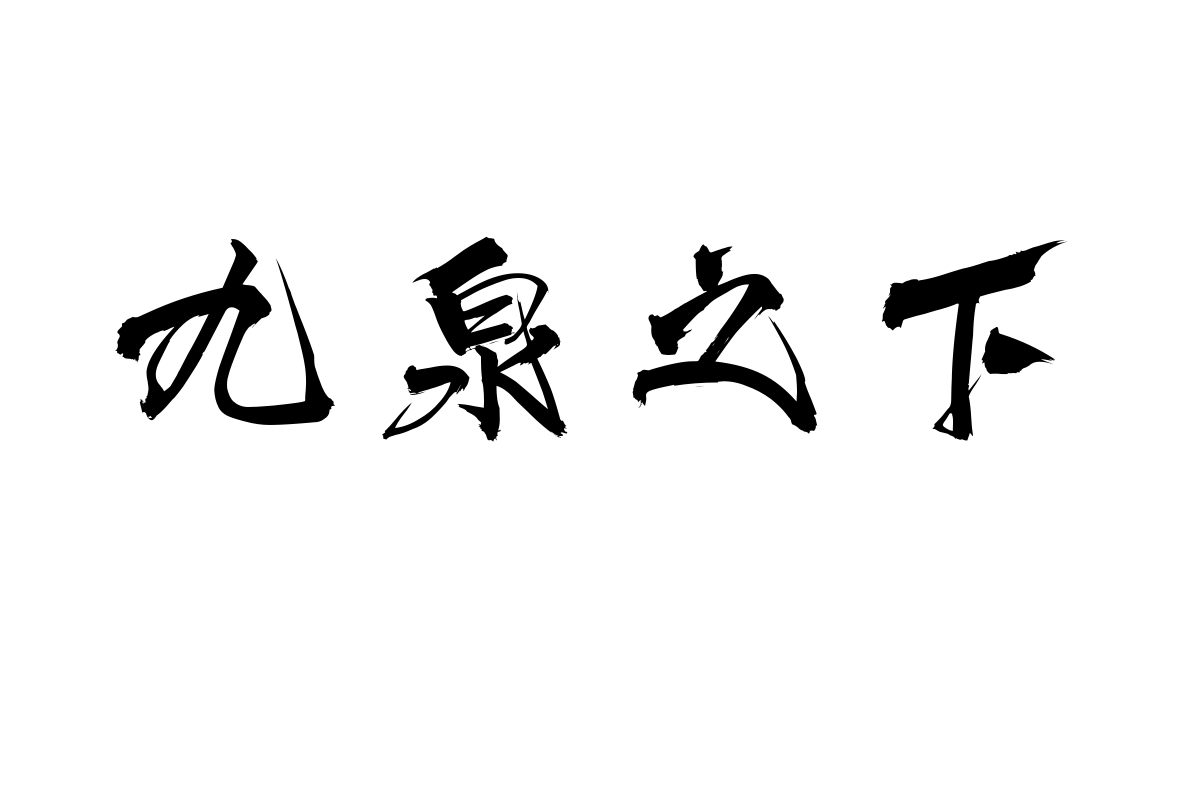
文道江湖体是一套具有独特风格的中文字体,由设计师根据传统书法艺术和现代设计美学相结合的理念创作而成。它的特点是笔画流畅、结构自然、风格古朴,适合用于各种需要展现传统文化韵味的场合。
1. 笔画流畅:文道江湖体的笔画线条流畅自然,给人一种优雅的感觉。这种流畅的笔画不仅使得字体美观,也使得阅读起来更加轻松愉快。
2. 结构自然:文道江湖体的字形结构自然,没有过多的装饰和复杂的线条。这使得字体看起来更加简洁大方,易于识别。同时,它也避免了过于繁复的字形,使得整体视觉效果更加和谐统一。
3. 风格古朴:文道江湖体的风格古朴典雅,充满了浓厚的传统文化气息。它很好地保留了传统书法的艺术特点,同时又不失现代设计的简洁性。这使得它在现代设计中具有独特的魅力。
4. 适用于多种场合:文道江湖体适用于各种需要展现传统文化韵味的场合,如书籍、海报、网页等。它的设计风格独特,能够吸引人们的注意力,让人印象深刻。
总之,文道江湖体是一款具有独特风格的中文字体,它以流畅的笔画、自然的结构、古朴的风格和广泛的应用场景,赢得了广大用户的喜爱和认可。